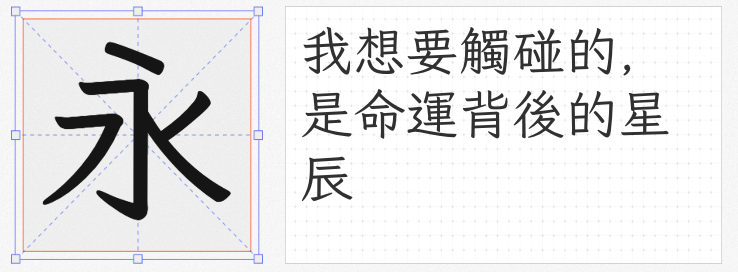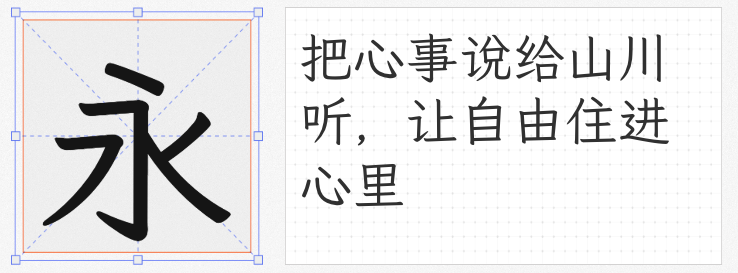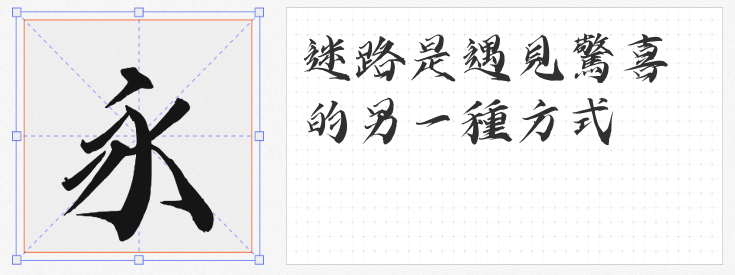
在国潮复兴与文化自信的浪潮下,手写字体以其独特的温度与艺术张力,成为设计领域的“点睛之笔”。本文精选四款免费商用的手写字体,涵盖古籍传承、日系混排、武侠创意、仿宋美学四大方向,助力设计师突破版权壁垒,释放创意潜能。
作为Klee One的第三次衍生字体,彭蠡文楷严格遵循《古籍印刷通用字规范字形表》(GB/Z 40637-2021),收录14,250个繁体汉字,字形规范统一,适用于古籍出版、传统书刊排版。其笔触端庄严谨,横竖撇捺间保留仿宋与楷体的双重韵味,既符合现代印刷标准,又传递出古籍的厚重感。
专为日语学习者与中日文混排设计,千菅书体以日本明朝体为基调,优先显示日标字形(如“視”“神”保留旧字体“⺬”部),同时兼容中文繁体。其笔画纤细流畅,转折处略带弧度,兼具楷体的规整与行书的灵动。
字屿云游手书以毛笔字为基底,通过局部形变与笔势外拓,构建出“流云萦绕剑锋”的视觉张力。其笔画粗细对比强烈,转折处锋芒毕露,结体紧致如松,既含蓄内敛又充满力量感。
作为Klee One的衍生字体,蒹葭楷F以《古籍印刷通用字规范字形表》为基准,字形接近仿宋活字设计,笔画纤细挺拔,结构严谨对称。其“横细竖粗”的笔画特征,与古籍中的雕版印刷字体高度契合。